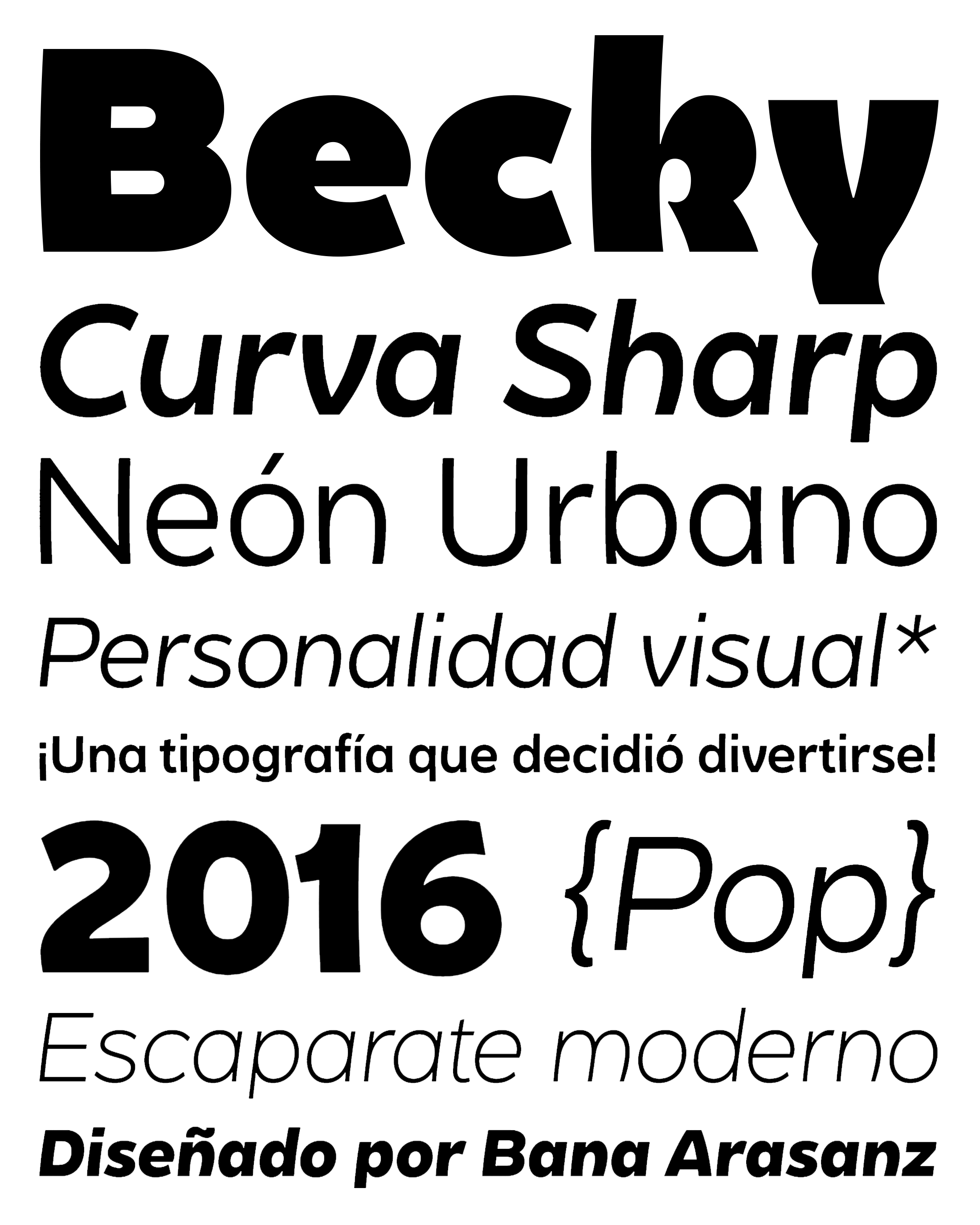
| Año | 2016 |
| Créditos | Bana Arasanz |
| Descripción | Becky es una tipografía display versátil, diseñada para atraer a un público joven, creativo y actualizado. Pensada especialmente para el mundo de la publicidad y el retail, resulta ideal para titulares de gran tamaño, branding, logotipos, publicaciones y textos breves. |
| Familia(s) | Becky Light, Becky Light Italic, Becky Regular, Becky Italic, Becky Medium, Becky Medium Italic, Becky Bold, Becky Bold Italic, Becky Extrabold, Becky Extrabold Italic |
| Estilos | 10 |
| Fundidora | W Type Foundry |